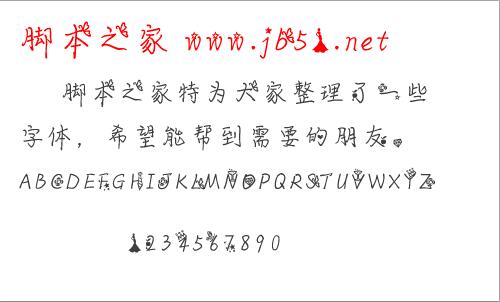
郭敬明字体小时代特别版是一款郭敬明手写风格的钢笔字体,并且是专门因小时代而推出的特别版,该字体不仅书写流畅,还添加了卡通花纹进行装饰,整体效果十分出色可以很好的应用于文本装潢、信息展示、网页设计、篆刻制模、数据制作、装潢设计、计算艺术设计、视觉设计、字帖等一切合法应用场景,有喜欢的朋友可免费下载收藏。